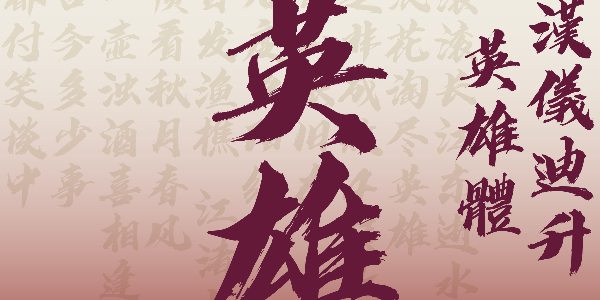
汉仪迪升英雄体
潇洒字如,英雄本色,汉仪迪升英雄体,是汉仪字库签约作者迪升于2018年创作的第一款手写体。飞扬而有力的字形,豪放而不羁的笔触,洋洋洒洒,有气吞山河之势。结构舒展,笔意连贯,书写的速度感形成笔画飞白增添了细节。这款字体作为标题字体富有视觉冲击力,适合影视娱乐等各类应用场景,彰显英雄气概。
字形飞扬而有力,左收右放。
笔墨豪放不羁,洋洋洒洒。
笔断意连,行笔连贯。
书写的速度感形成笔画飞白,细节丰富。
汉仪迪升英雄体的西文部分同样潇洒有力,笔断意连,间以飞白。覆盖了日文假名以满足更广泛的使用场景。